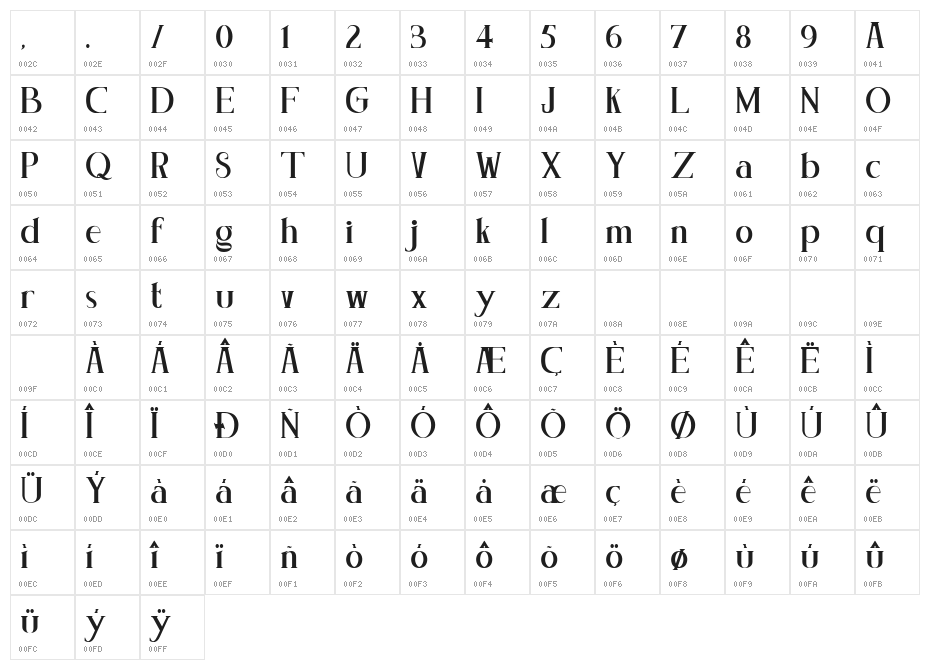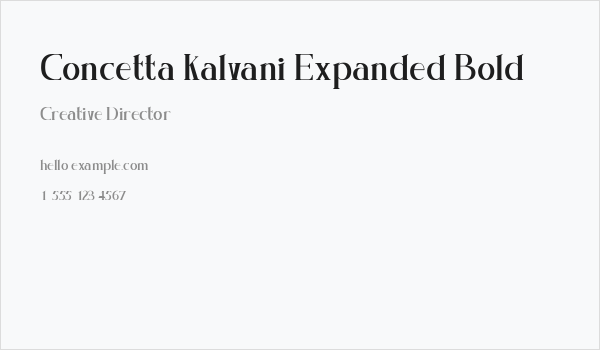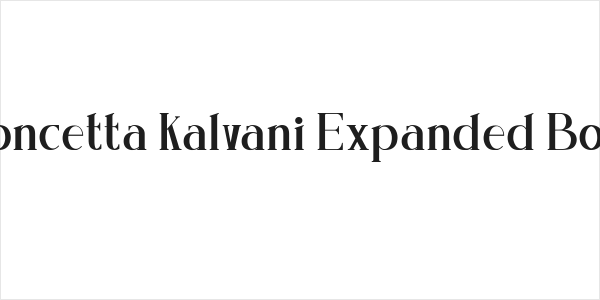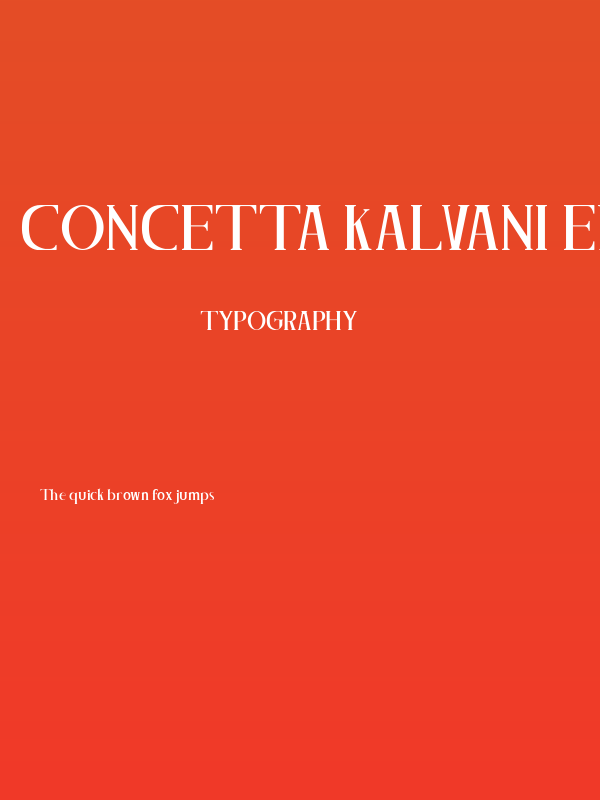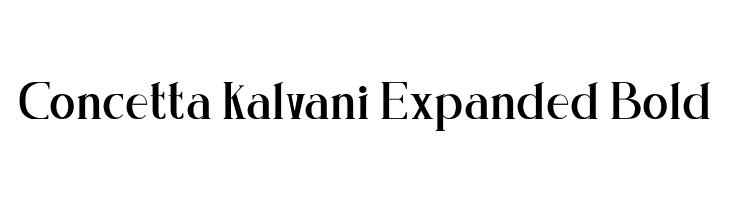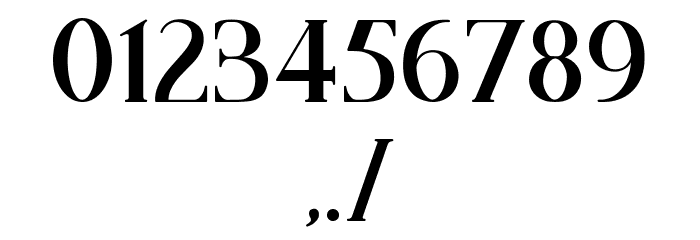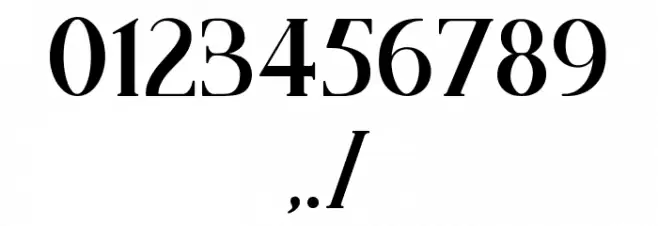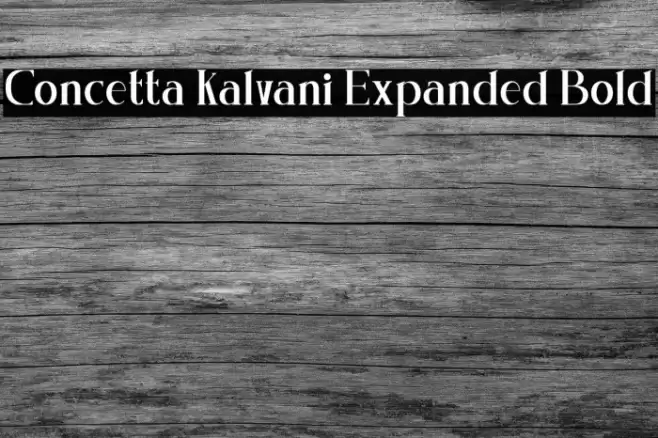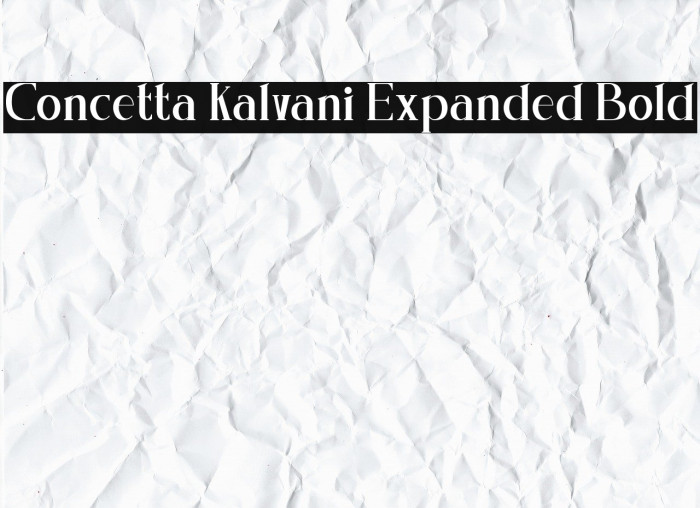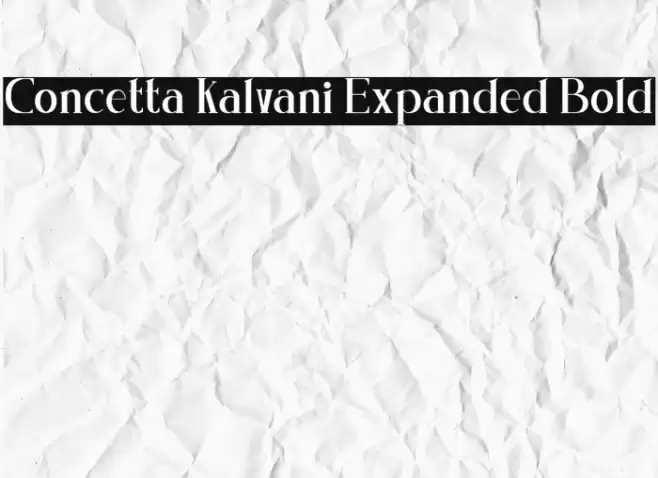
Concetta Kalvani Expanded Bold Font
| Nom | Concetta Kalvani Expanded Bold |
| Famille de police | Concetta Kalvani |
| Poids | Expanded Bold |
| Largeur | Expanded |
| Projets proposés | Ideal for headlines, branding, posters, and editorial design where a strong, sophisticated presence is desired. |
| Auteur | Fonts by william jhordy |